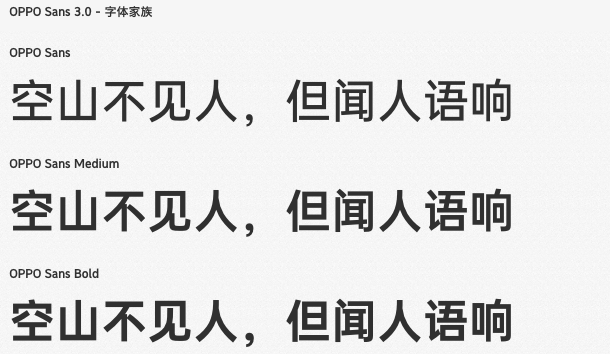
在追求设计美感与功能性的道路上,选择合适的字体至关重要。今天,为大家推荐两款可免费商用的黑体字体家族——“HarmonyOS Sans SC”与“OPPO Sans 3.0”,它们不仅各具特色,还完美融合了人文与现代元素。
“HarmonyOS Sans SC”字体家族在保障字体体验的功能性前提下,巧妙地找到了人文与现代之间的平衡。其短笔画保持横平竖直,简约无装饰,而长笔画中则融入了书法的笔势美学,这种设计不仅保持了字体的易读性,更赋予了它独特的艺术魅力。该家族共有6款字体,满足了不同场景下的使用需求。
另一款值得推荐的字体家族是“OPPO Sans 3.0”。作为OPPO的专属品牌字体,OPPO Sans 3.0采用了全新的骨架设计,中宫自然舒适,结构稳定且字形舒展。这样的设计不仅强化了屏幕显示的易读性和外观性,更体现了科技美感。简洁真实的风格,让人在使用时感受到一种清新脱俗的气息。该家族共有3款字体,每一款都充满了OPPO品牌的独特韵味。
无论是“HarmonyOS Sans SC”还是“OPPO Sans 3.0”,它们都以独特的风格和卓越的功能性,成为了设计师们的心头好。在追求设计美感的同时,不妨试试这两款免费商用的黑体字体家族,相信它们会为您的作品增添一份独特的魅力。